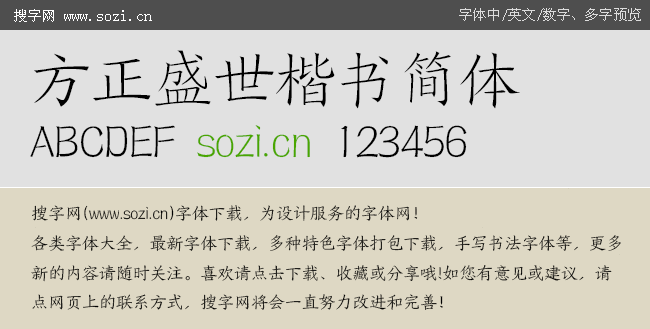
方正盛世楷書(shū)簡(jiǎn)體
搜字網(wǎng)提供一款方正盛世楷書(shū)簡(jiǎn)體中文字體下載,方正盛世楷書(shū)簡(jiǎn)體是一款端正的楷體字體,字體大方得體,效果非常漂亮,可以應(yīng)用于美術(shù)設(shè)計(jì)、宣傳海報(bào)、書(shū)籍設(shè)計(jì)等領(lǐng)域。